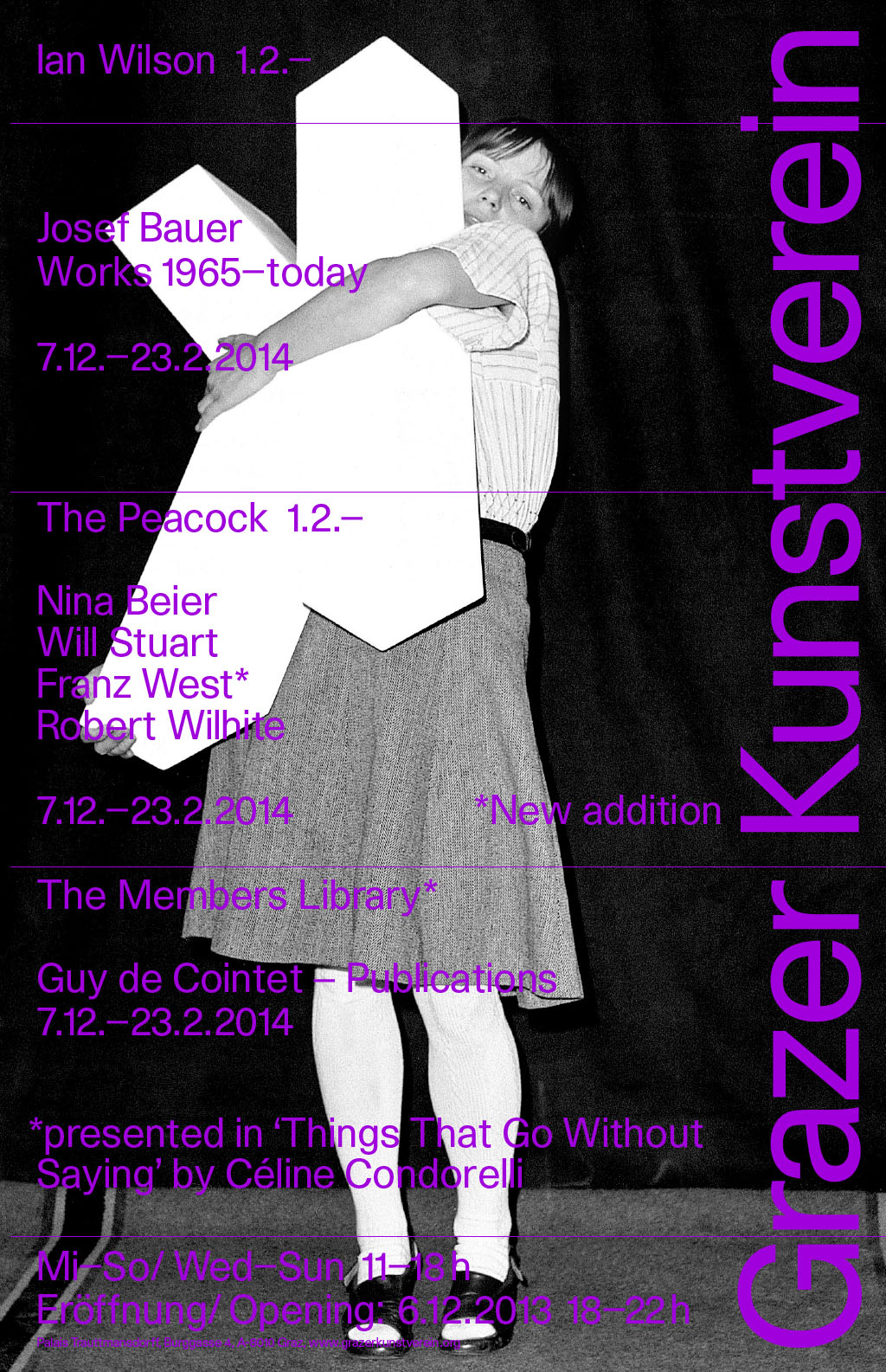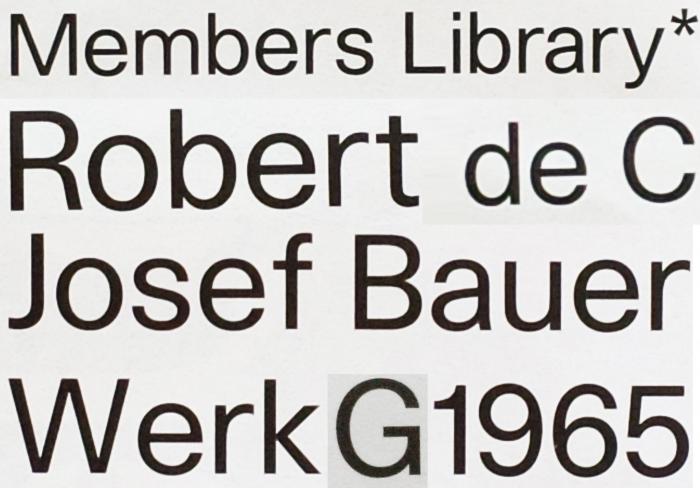
Wer löst das Schrift-Rätsel?
welche Schrift könnte das sein?
Sie ähnelt stark AG Book, Arial oder Neue Haas Grotesk jedoch stimmen die Großbuchstaben "R", "G", das kleine "a" oder der "*" im Detail nicht überein. Kennt jemand diese Schrift?
Gelöst von Albert-Jan Pool
Haas Unica von Team ’77 / André Gürtler, Christian Mengelt, Erich Gschwind
Die Schrift wurde für die frühere Haas’sche Schriftgießerei entwickelt, es gab sie für die ehemalige Fotosatzsysteme von Autologic, Linotype und Scangraphic. Scangraphic brachte ca. 1991 eine PostScript version heraus, die später von Elster & Flake (eventuell neu konvertiert, weiß ich nicht mehr) vertrieben wurde. Die Rechte von Haas waren auf Linotype übergegangen und nach einer lizenzrechtliche Auseinandersetzung wurde die PostScript-version vom Markt zurückgezogen.
Es handelt sich in diesem Fall möglicherweise um die einst von Scangraphic / E&F verkaufte Schrift oder eine Raubkopie davon, oder jemand anders hat sie inzwischen auch digitalisiert.